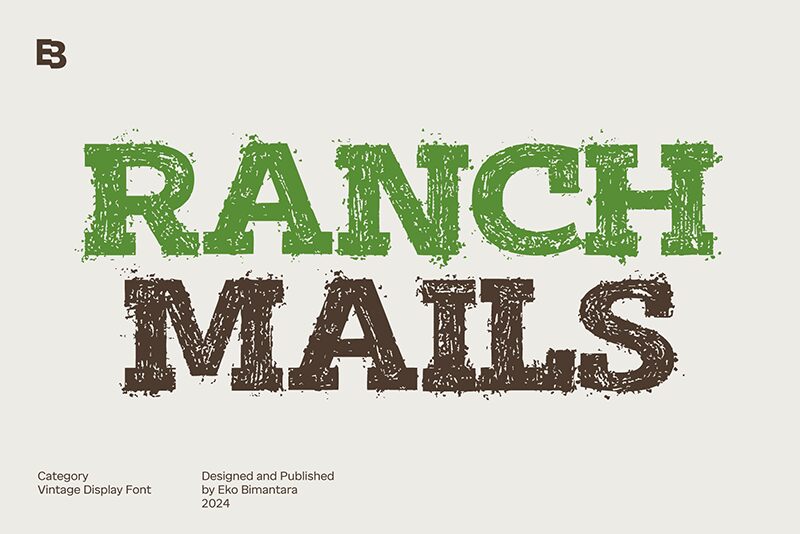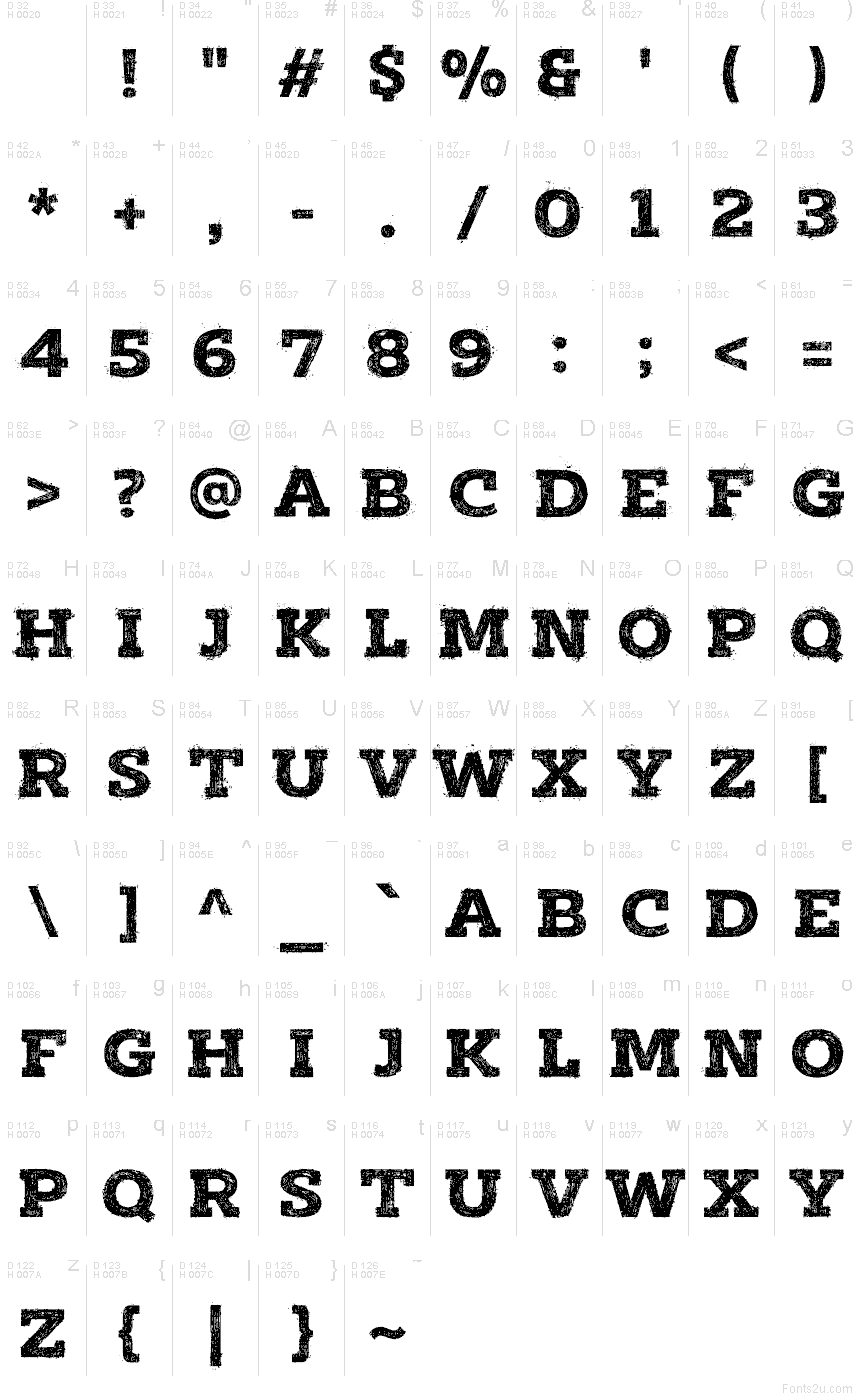
La tipografía Ranch Mails de Eko Bimantara es una fuente de estilo grunge audaz que combina bordes definidos con detalles desgastados aleatorios. Sus formas de letras expandidas le otorgan una presencia imponente que puede resultar muy útil para crear titulares exitosos. Todos los diferentes atributos de la tipografía contribuyen a su aspecto robusto y a su imagen de inspiración vintage.
Los posibles usos de esta fuente de visualización gratuita incluyen portadas de álbumes, portadas de libros, carteles, pegatinas, diseños de insignias y pines, texto de titulares para folletos y volantes, impresiones en camisetas y diseños de marca de ropa en general, así como diseños de tarjetas de presentación elegantes. Ranch Mails también es apropiada para usos en pantallas, como títulos en diseño web o edición de video.